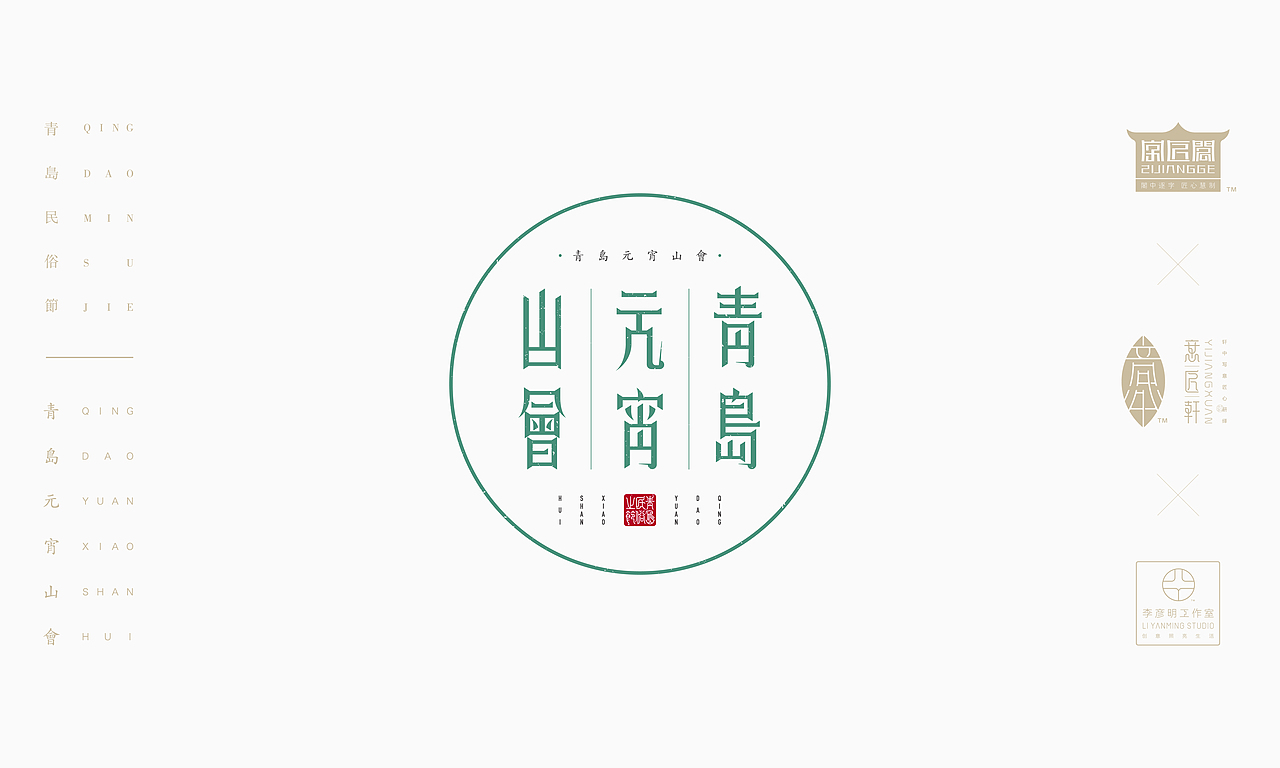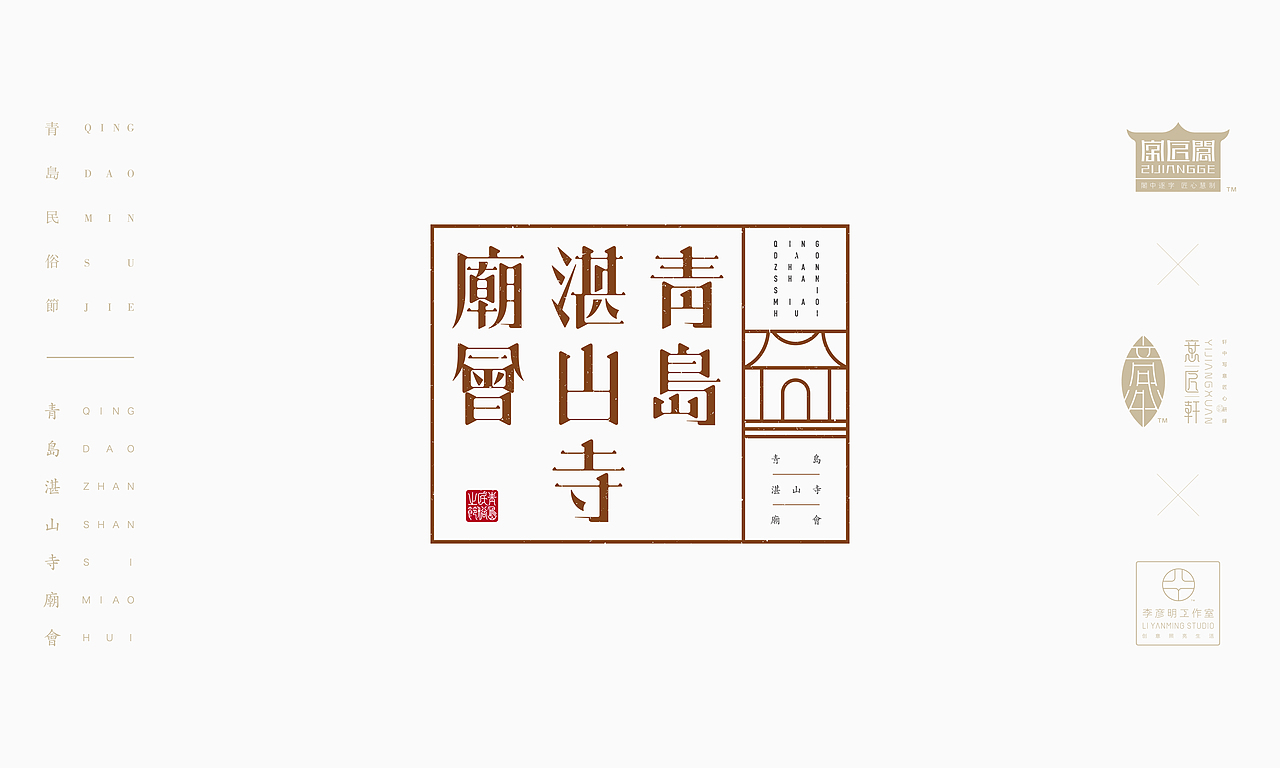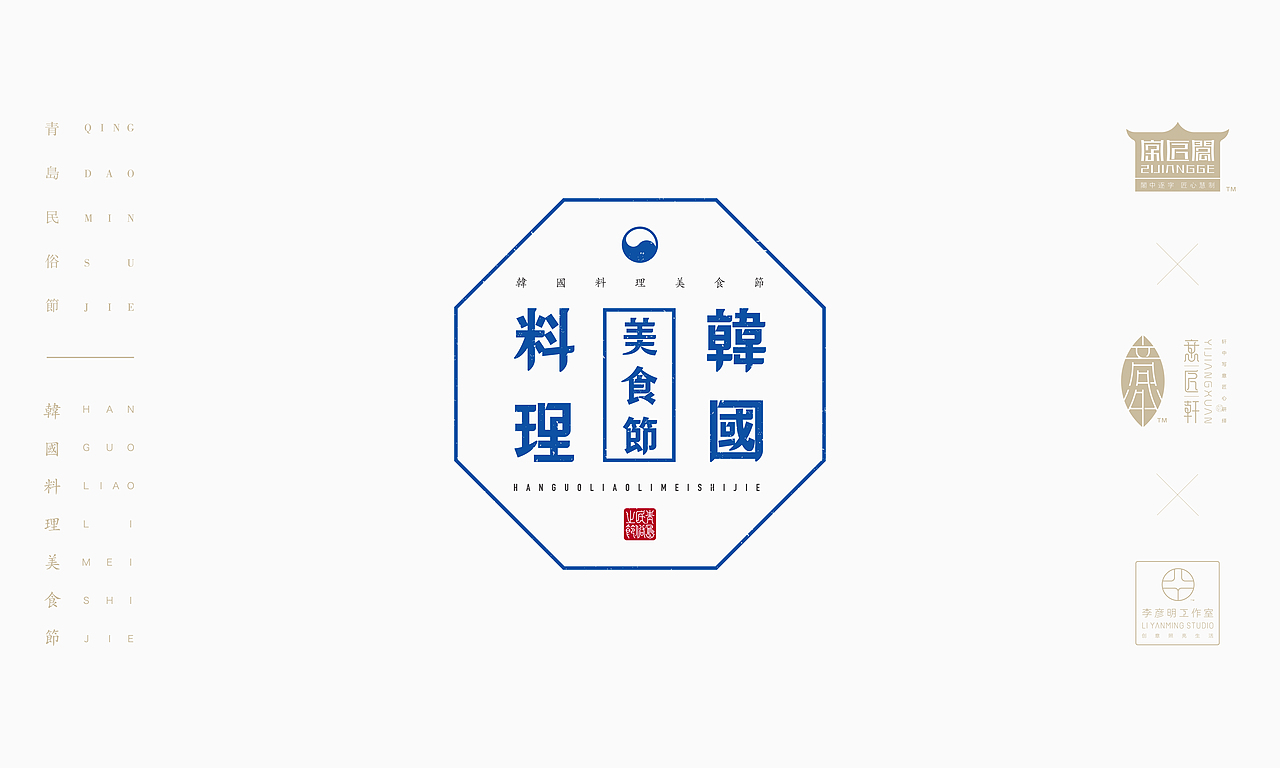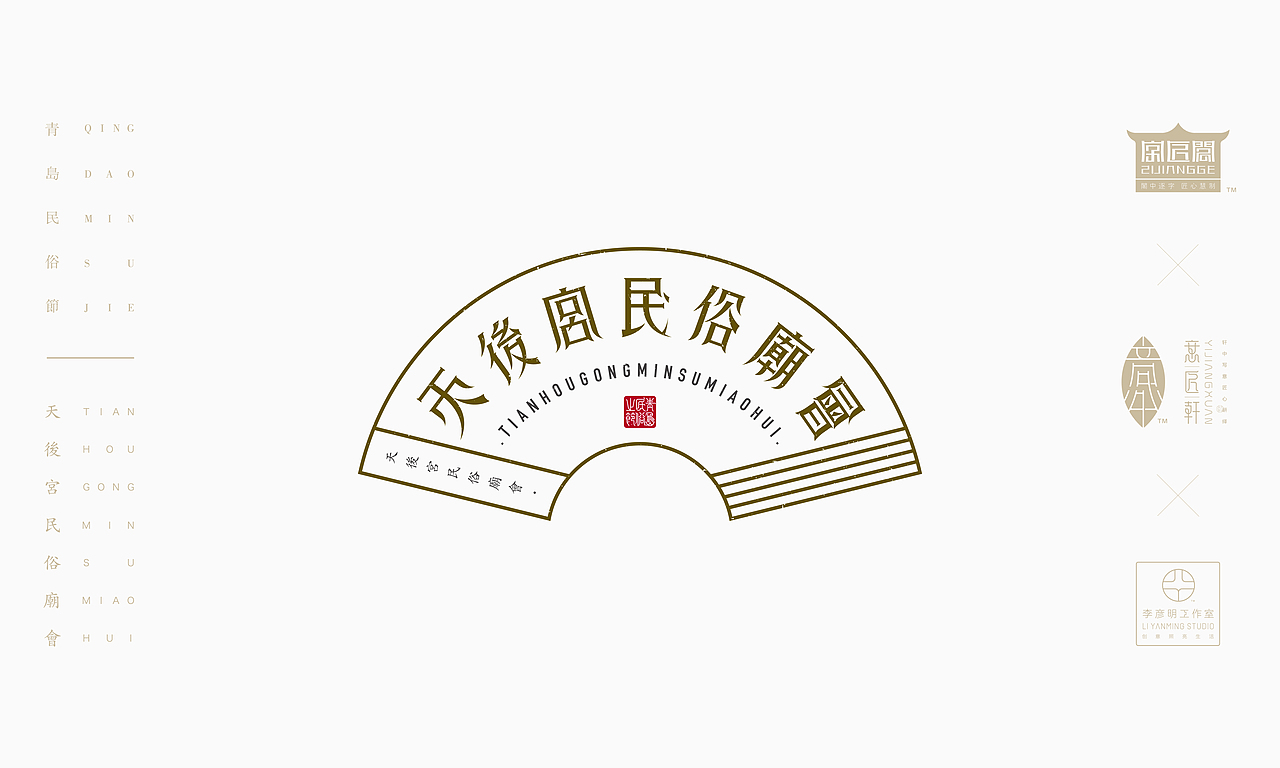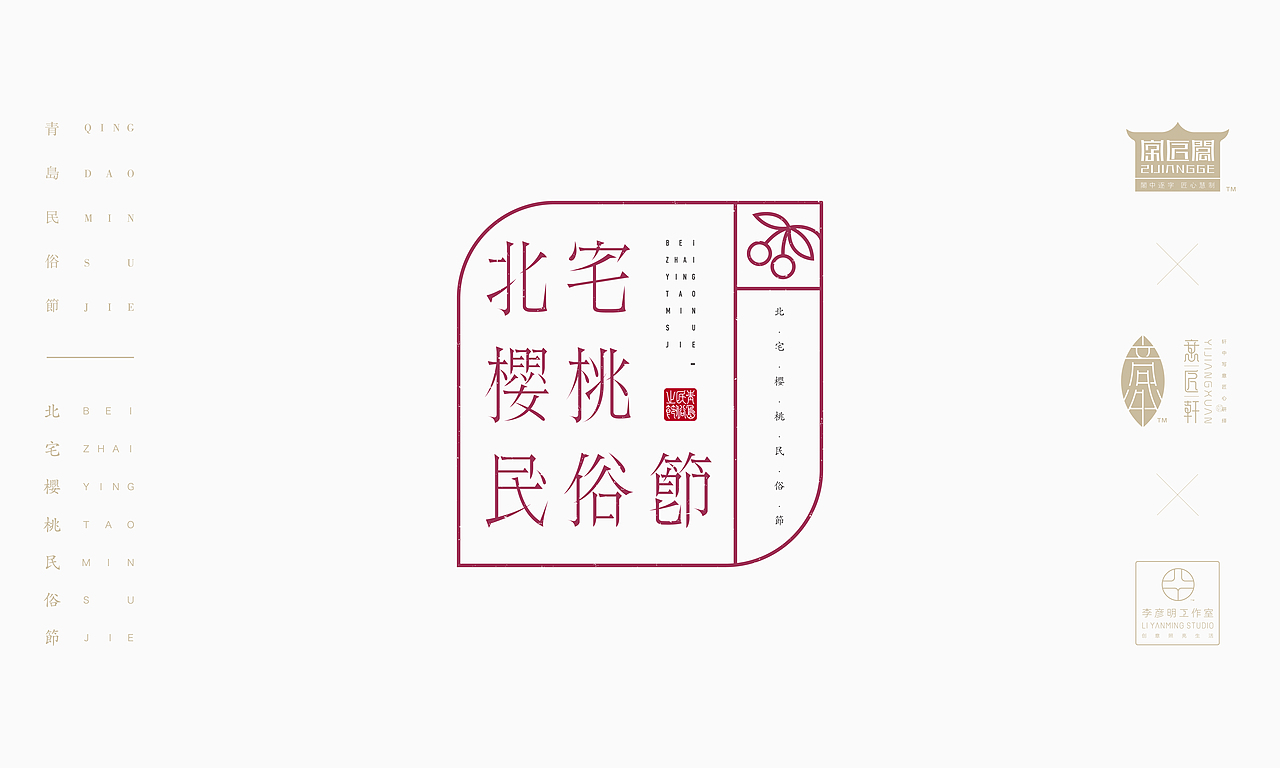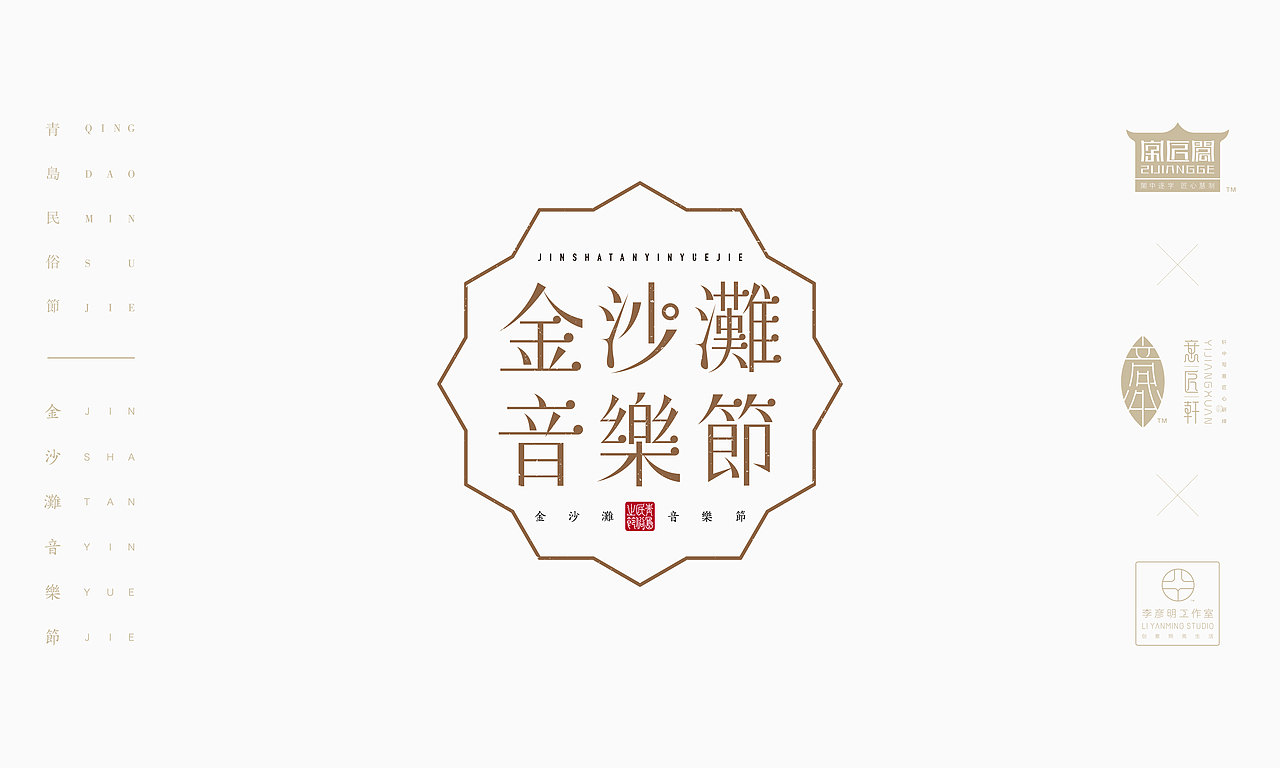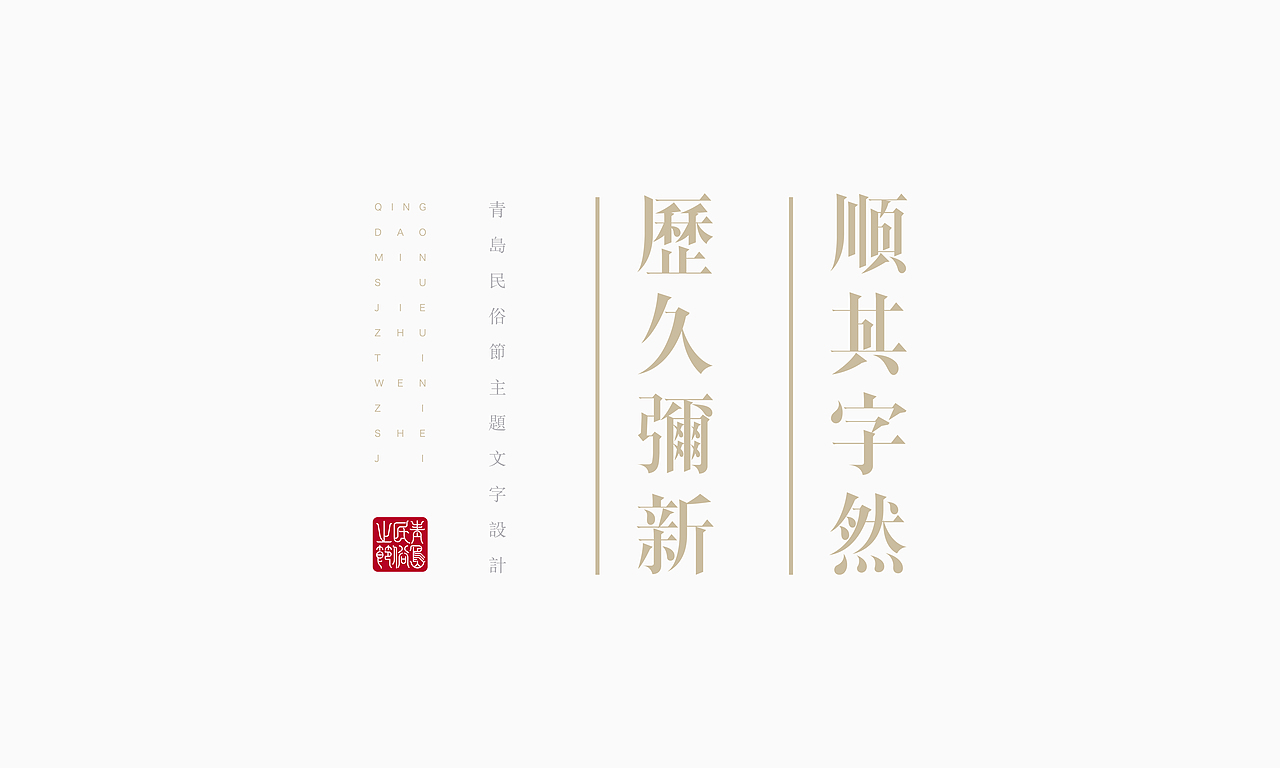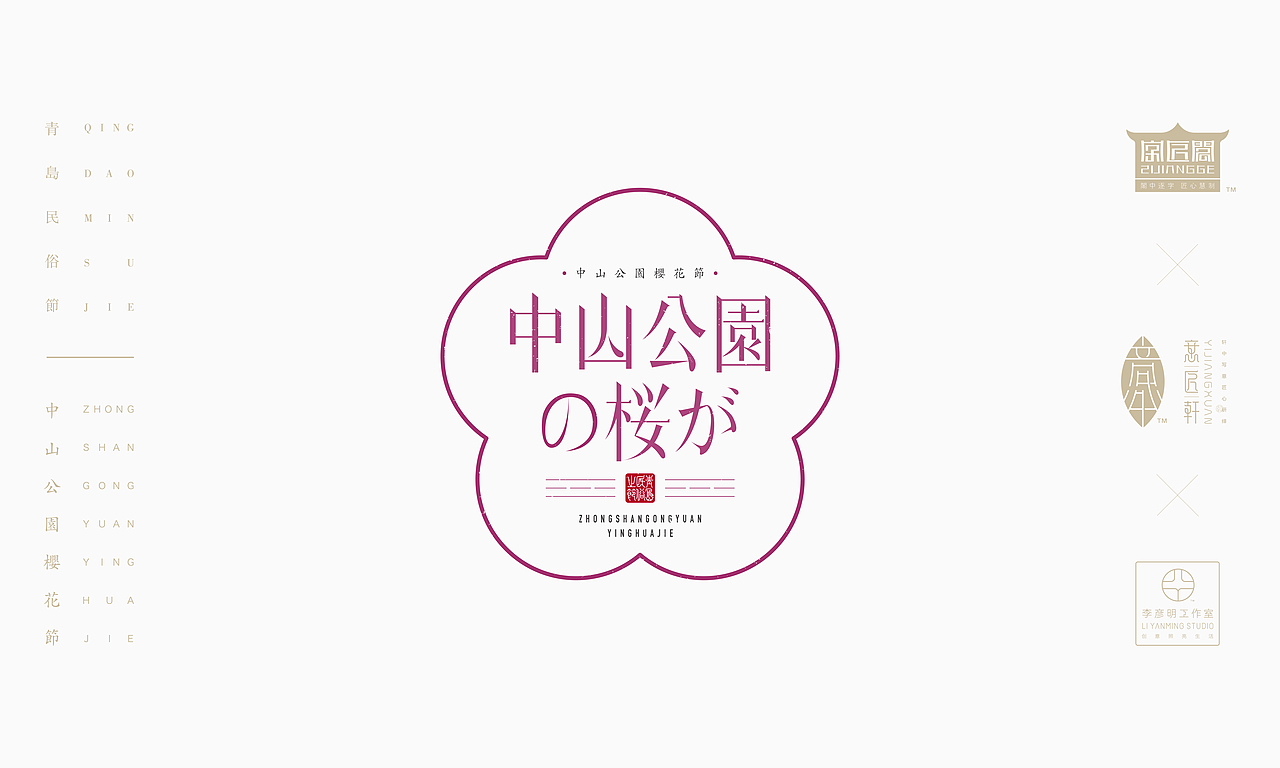
《“青岛民俗节”主题文字设计》
// 青岛,一所美丽的海滨城市。求学七年,回忆满满!伴着海浪的余音,深处记忆涌上手头…
// 这是一次以“青岛民俗节”为主题的文字设计之旅,20个“青岛民俗节日”的名字设计跃然纸上。这不仅仅是纯粹的文字,更是内心中对于每一个民俗节日的理解与刻画…
// “青岛民俗节”主题文字设计,以纯文本文字设计为主,稍加图案辅助,形态上以图文并茂的形式呈现。20个“青岛民俗节日”的名字设计,情态表达上以经典、恒久、新颖、简约为基调,精神追求上以“汲古融新,质朴纯真”为诉求…
// 该款文字设计,以“顺其字然,历久弥新”来定位,再恰当不过…
// 接下来让我们一起进入“青岛民俗节”为主题的文字设计…
《田横祭海节:渔民过的节日,发源于山东省田横镇周戈庄村的地方传统民俗活动,具有500多年历史。2008年,田横祭海节被列入第二批国家级非物质文化遗产名录,并荣膺首届节庆中华奖“最佳公众参与奖”…》
《中山公园樱花节:已有80余年的历史,每年4、5月间在中山公园举行,20世纪30年代,中山公园的赏樱活动已有盛名,"东海花海"被列为青岛市十景之一…》
《青岛湛山寺庙会:是青岛地区最著名的佛家庙会。每年农历四月初八日(佛祖释迦牟尼生日)开庙逢会3天。届时,善男信女、旅游观光者络绎不绝,热闹非凡…》
《金沙滩音乐节:坐落于青岛黄岛,作为当前中国最大型的免费户外音乐节和山东历史上规模最大的专业户外音乐节,成为了乐迷们每年集体朝奉的节日…》
《中国国际时装周:自2001年至今已连续成功举办七届,每年9月举办,定位为“未来时装设计大师的摇篮”、“新锐时尚品牌的诞生地”…》
《青岛酒吧文化节:自1998年以来,青岛酒吧文化节迄今已连续举办了五届,在海内外产生了一定的影响,并逐步成为青岛冬季旅游的升温点,主要有主题酒吧活动、名人鸡尾酒会、摄影大赛、调酒大赛等活动…》
《海云庵糖球会:因庙会上卖山楂糖球的特别多,久而久之,便习称为"海云庵糖球会"。近20年来,海云庵糖球会成为远近闻名的大型民俗庙会, 2005年被评为“中国十大民俗节会”之一…》
《天后宫民俗庙会:俗称青岛大庙庙会,是集祭祀、歌舞、文娱、商贸于一体的汉族传统民俗活动。属于道家庙会,位于青岛市太平路19号。天后宫庙会寄托了汉族劳动人民一种辟邪除灾、迎祥纳福的美好愿望…》
《青岛国际海洋节:创始于1999年,旨在传播奥林匹克精神,现已成为促进全球海洋科技、滨海旅游、海洋文化、水上运动等领域沟通合作的平台。同时,海洋节也是青岛夏日一道亮丽的风景线,吸引着八方宾朋…》
《十梅庵梅花节:青岛十梅庵,被誉为“梅花的故乡”,是中国江北第一梅园。梅花节的主要内容有梅花,蜡梅大、中、小型盆景,露地景地(梅树),梅花、蜡梅写意盆景,插花艺术,摄影展,诗书画展等…》
《大泽山葡萄节:位于青岛平度大泽山镇,时间为一个月,横跨不同品种葡萄的盛果期,游客可以品尝到各种葡萄的美味。因此,大泽山被誉为“中国葡萄之乡”…》
《清溪庵萝卜会:是历史悠久的民俗活动。逢庙会日,人们来这里卖萝卜、买萝卜、吃萝卜,久而久之,清溪庵庙会就被人们称为“萝卜会”。 近年来,又举行了现场雕刻萝卜比赛和萝卜艺术雕刻展览会…》
《青岛国际啤酒节:始创于1991年,在每年8月的第二个周末开幕,为期16天,是亚洲的啤酒盛会。如今,啤酒节已经成为彰显青岛城市个性优势与魅力的盛大节日,以啤酒为媒介,展现了青岛啤酒公司和城市…》
《韩国料理美食节:走在青岛的大街小巷,无处不感到“韩流”的存在,富丽的韩国驻青总领事馆、正宗的韩国料理、韩式住宅、韩国城、韩国服装行、中韩歌会、韩国周活动、韩语新闻节目、韩语版杂志…》
《青岛元宵山会:已成为青岛市春节期间重要的民俗文化活动,享有青岛新春第一节的美誉,赢得百姓的喜爱。每年节会期间,举办盛大在具有浓郁的民俗民间特色的开幕式,平均年参与人数达百万人次…》
《城阳牡丹艺术节:位于青岛天香园内,以牡丹、芍药为主,广植园内,花季时节,埋怨锦簇。园内有人工湖,石桥、凉亭。整个园林以古典风格为主…》
《李沧民俗赏花会:以"魅力青岛,和谐李沧"为主题,以"弘扬民俗文化、盛赞改革开放"为契机。活动分为文艺活动、民俗文化、民间饮食文化和商贸活动四大板块,十二项内容…》
《新正民俗文化庙会:是青岛传统民间延袭了几百年的传统年俗中的一项典型集体活动,是以妈祖信仰为依托的祭祀习俗,与青岛地区地方民风民俗紧密结合,具有浓郁的地方传统特色…》
《北宅樱桃民俗节:"红了樱桃,富了百姓"。"北宅素有'中国樱桃之乡'的美誉,北宅种植樱桃有一百多年的历史,作为青岛市十大节会之一的青岛北宅樱桃节,自1996年来已成功举办了17届,成为北宅街道生态旅游的龙头…》
《胶州秧歌民俗节:又称“地秧歌”、“跑秧歌”;民间称“扭断腰”、“三道弯”,是山东省三大秧歌之一。1991年的“中国首届秧歌大赛”中,胶州秧歌获优秀奖…》
《“青岛民俗节”主题文字设计:纯文本文字设计1...》
《“青岛民俗节”主题文字设计:纯文本文字设计2...》
《“青岛民俗节”主题文字设计:顺其字然,历久弥新...》